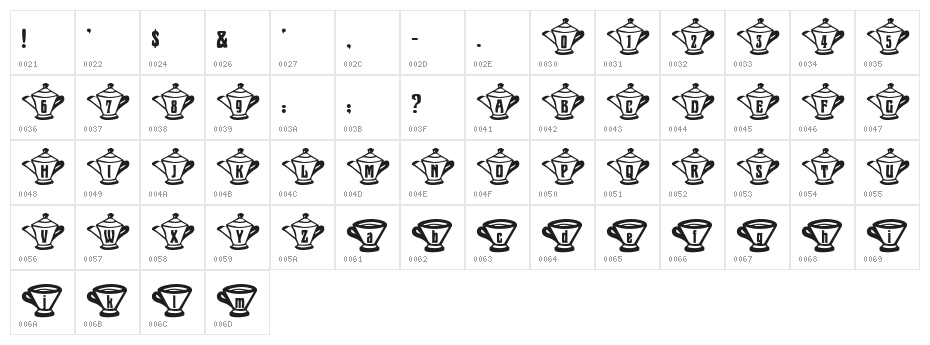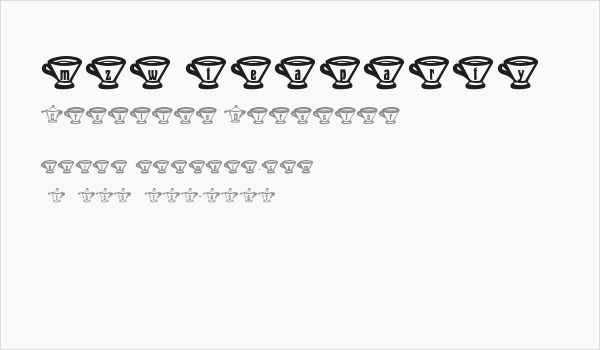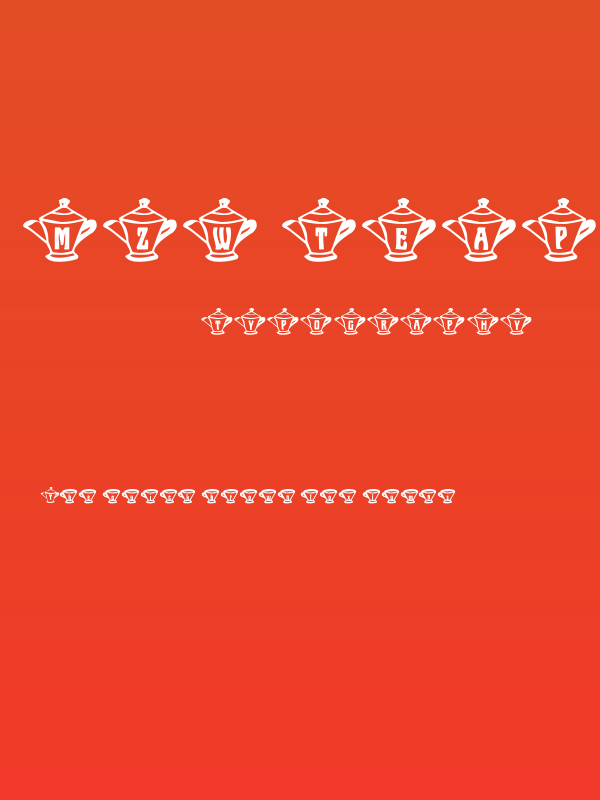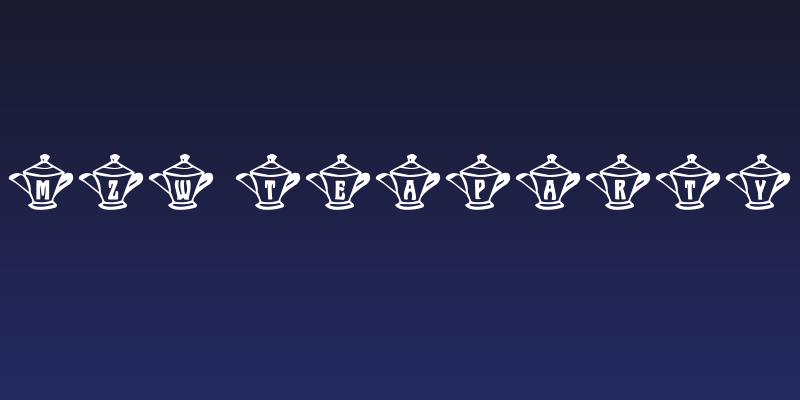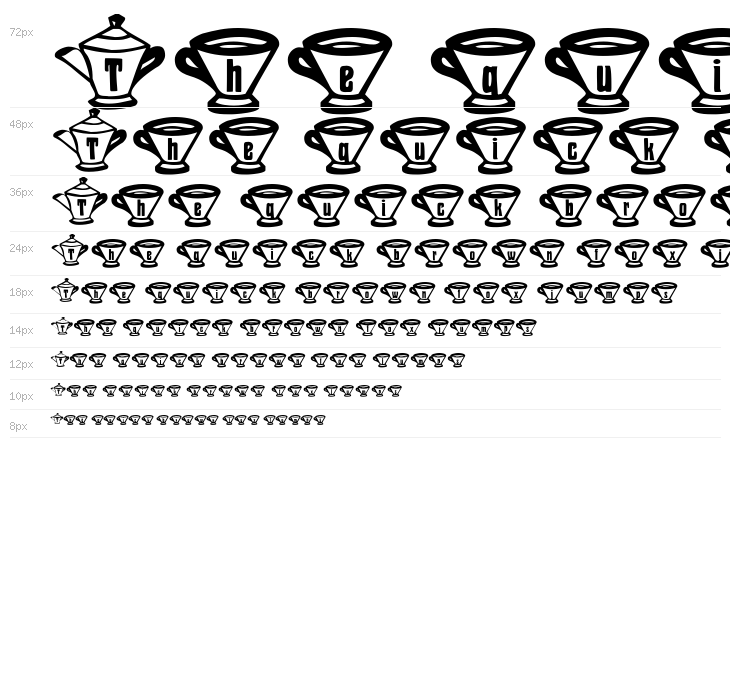
mzw teaparty Font
| Anwendungsfall | Logos, Headlines, Invitations |
| Vorgeschlagene Projekte | Ideal for tea-themed events, children's book covers, playful invitations, and novelty product packaging. |